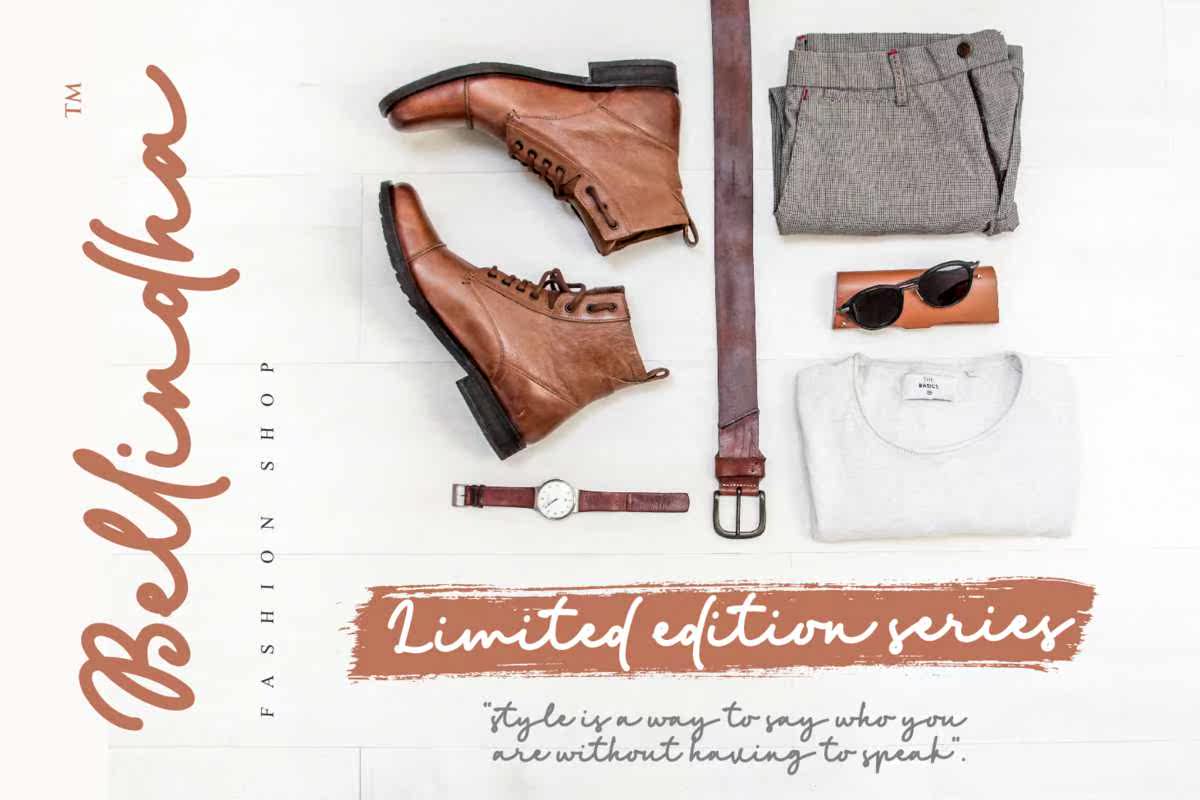
Golden Blasts是一个带有Anatural&StyleishFlow的脚本上的金色签名。该脚本集是个性化品牌的完美之选。它的目的是为您的个性化品牌服务。但是,该功能适用于所有应用程序。从个性化品牌、照片签名、产品包装、,广告可以从这一系列的粗体签名中获益。GoldenBlast是一个具有自然和风格流的脚本中的粗体签名。这一系列的脚本非常适合个人品牌。它的目的是为您的个人品牌服务。但是,这项工作适用于所有应用。从个人品牌、照片签名、产品包装、,广告可以从这一系列的粗体签名中获益。